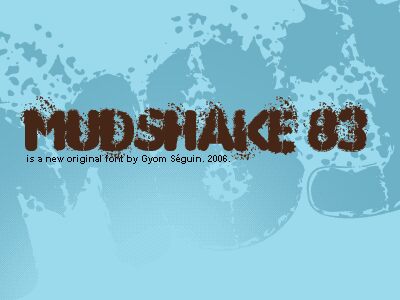
Mudshake 83 di Gyomsegs è un carattere display gratuito ed eroso, le cui forme nere e ampie sembrano esplose a causa di lacune sparse e rotture verticali grezze. L'effetto di logoramento non è un semplice filtro superficiale; scava a fondo nelle lettere, donando all'intero design una texture fangosa e schizzata che resta densa anche dove parti della superficie si sgretolano.
Questa consistenza maltrattata conferisce ai titoli brevi un carattere crudo, perfetto per poster, flyer musicali, grafiche horror, titoli di videogiochi e packaging grunge. È ideale per dare carattere a promozioni di eventi o copertine, dove i bordi consumati e l'aspetto frammentato devono sembrare incisi nelle lettere, piuttosto che semplicemente stampati sopra.